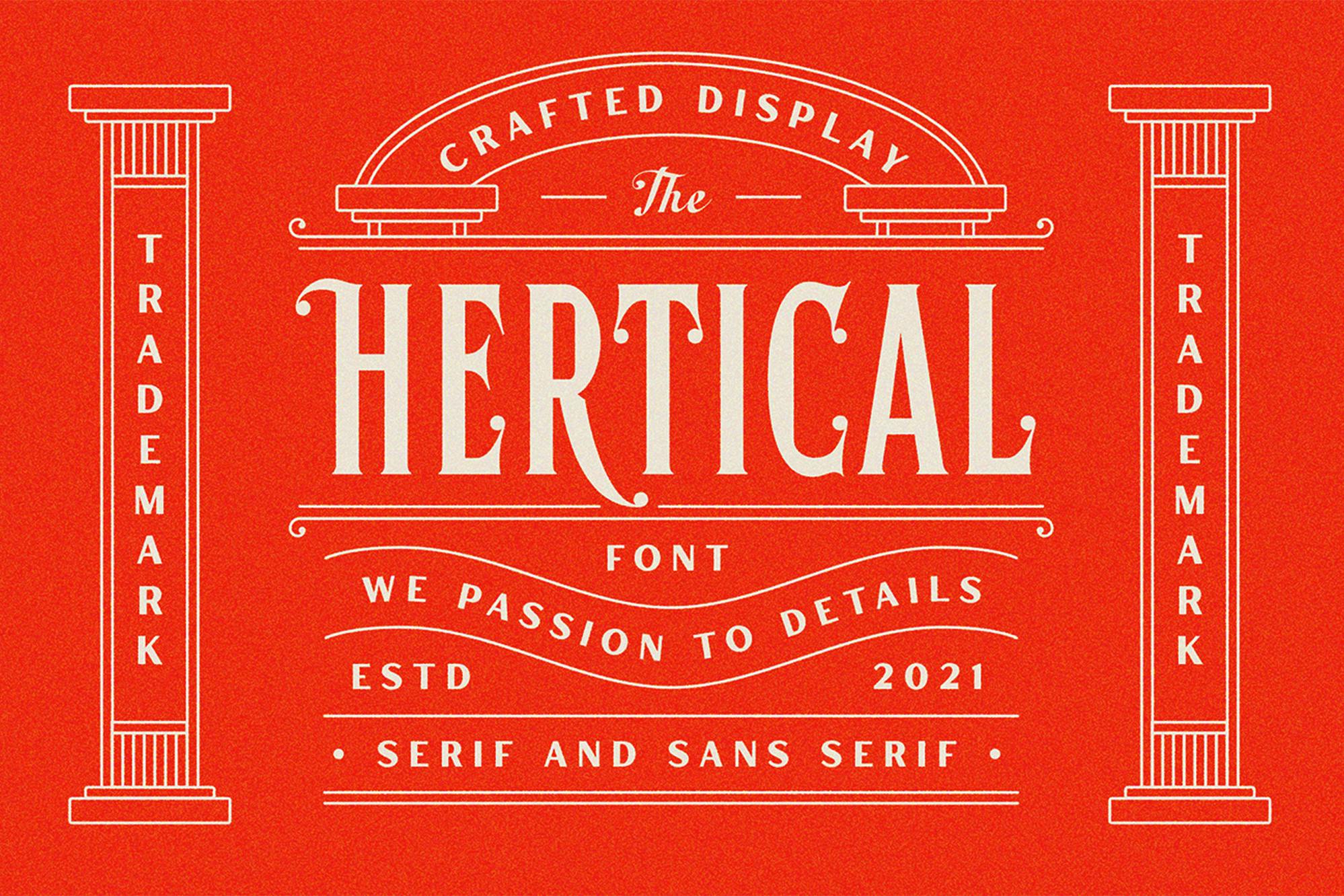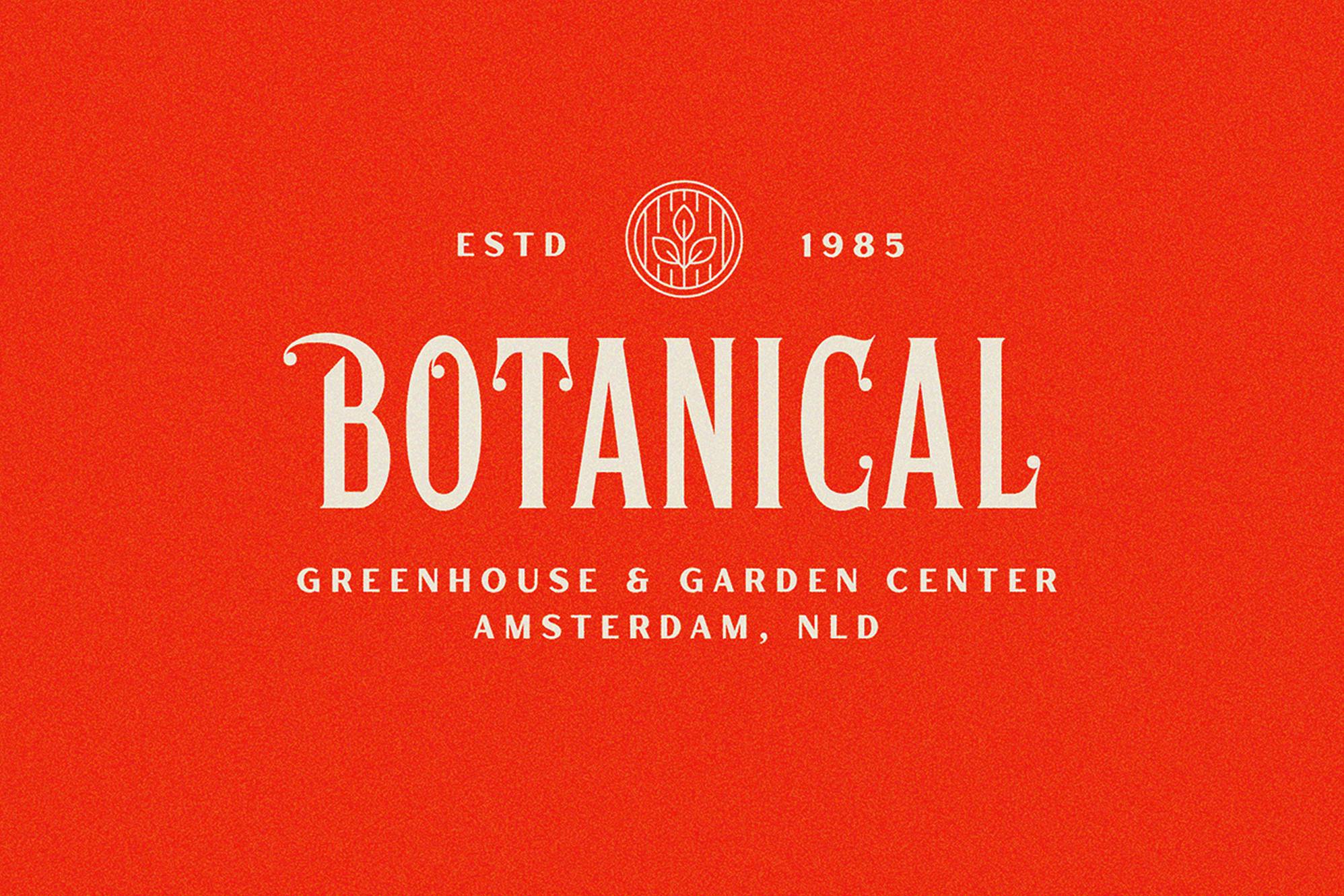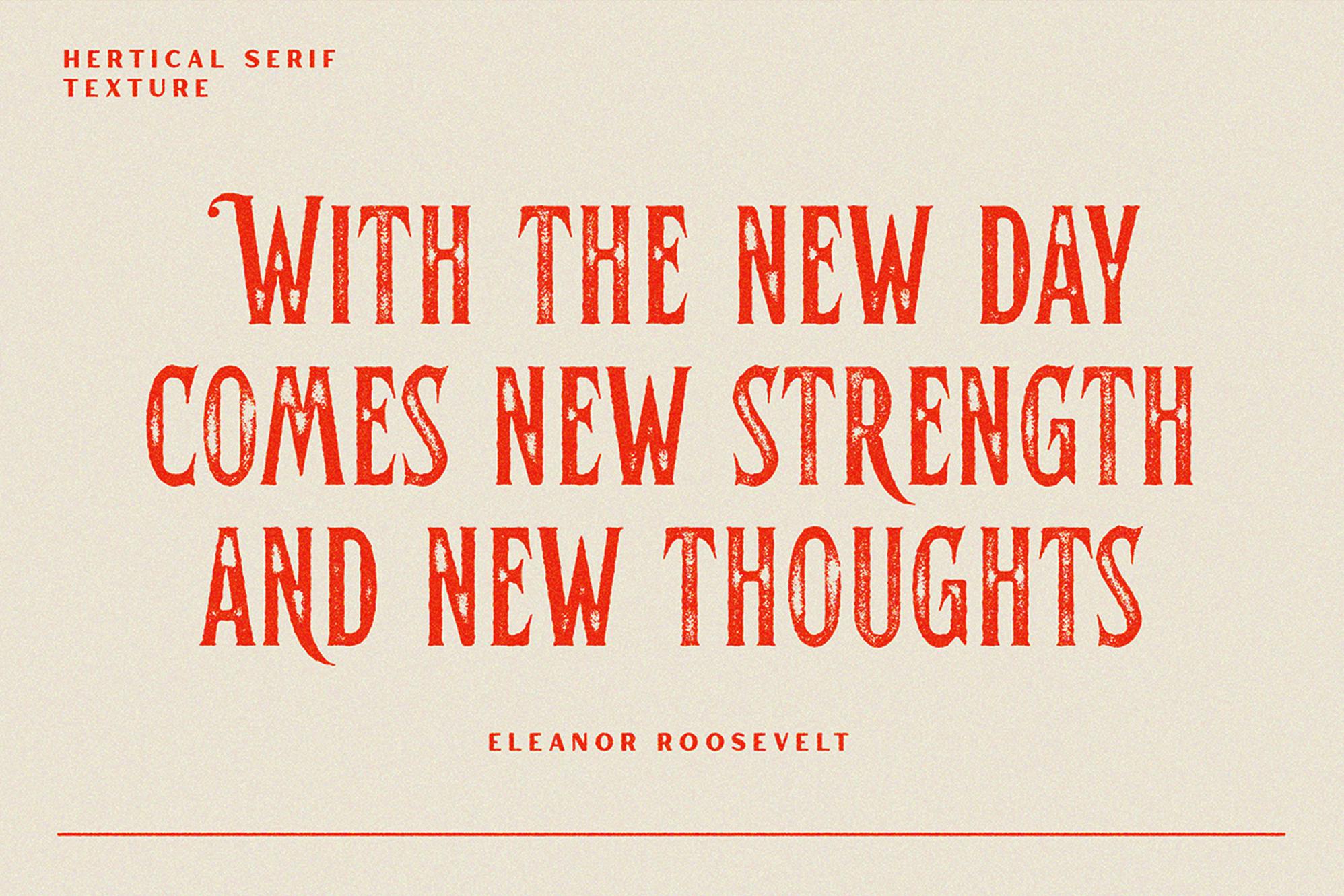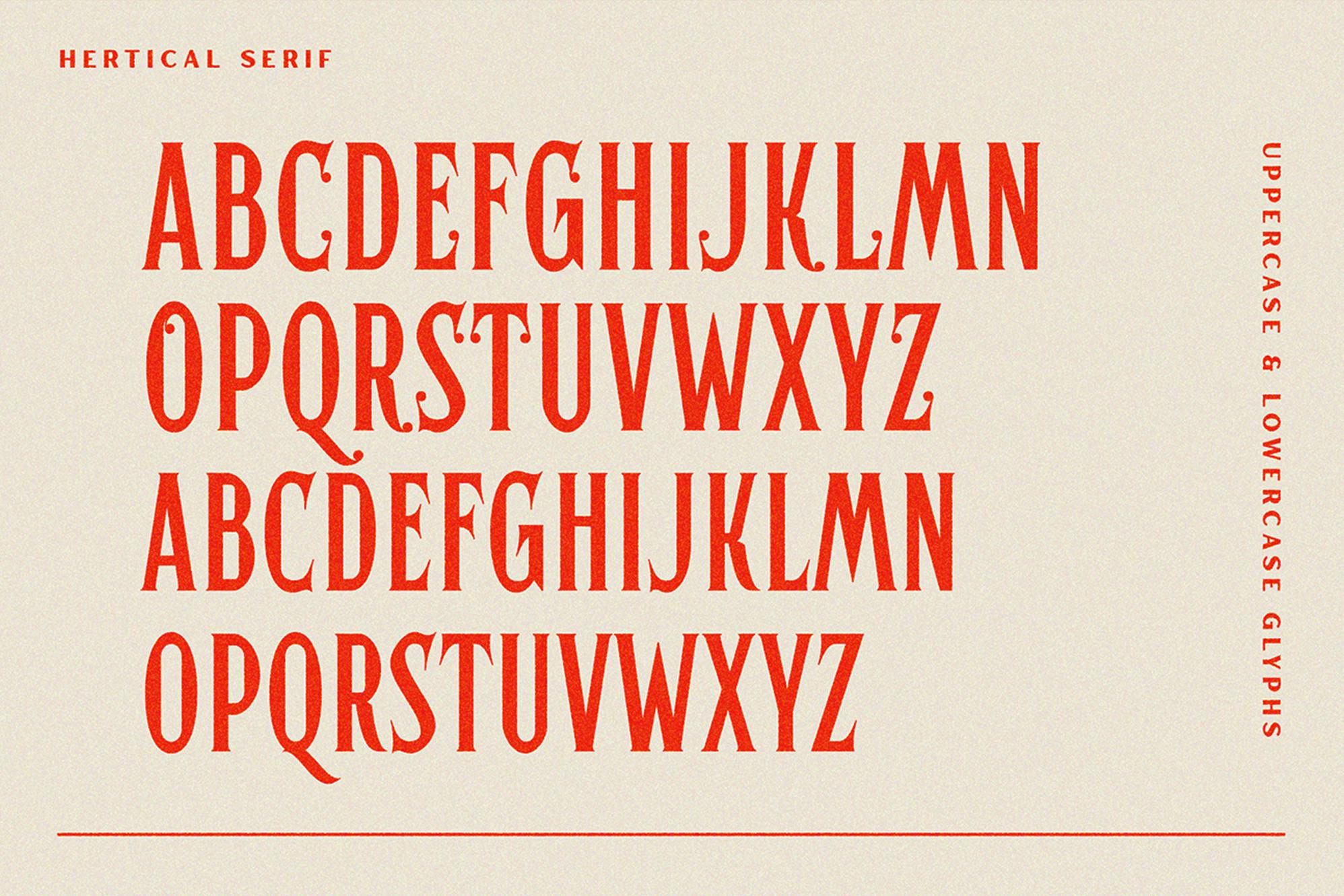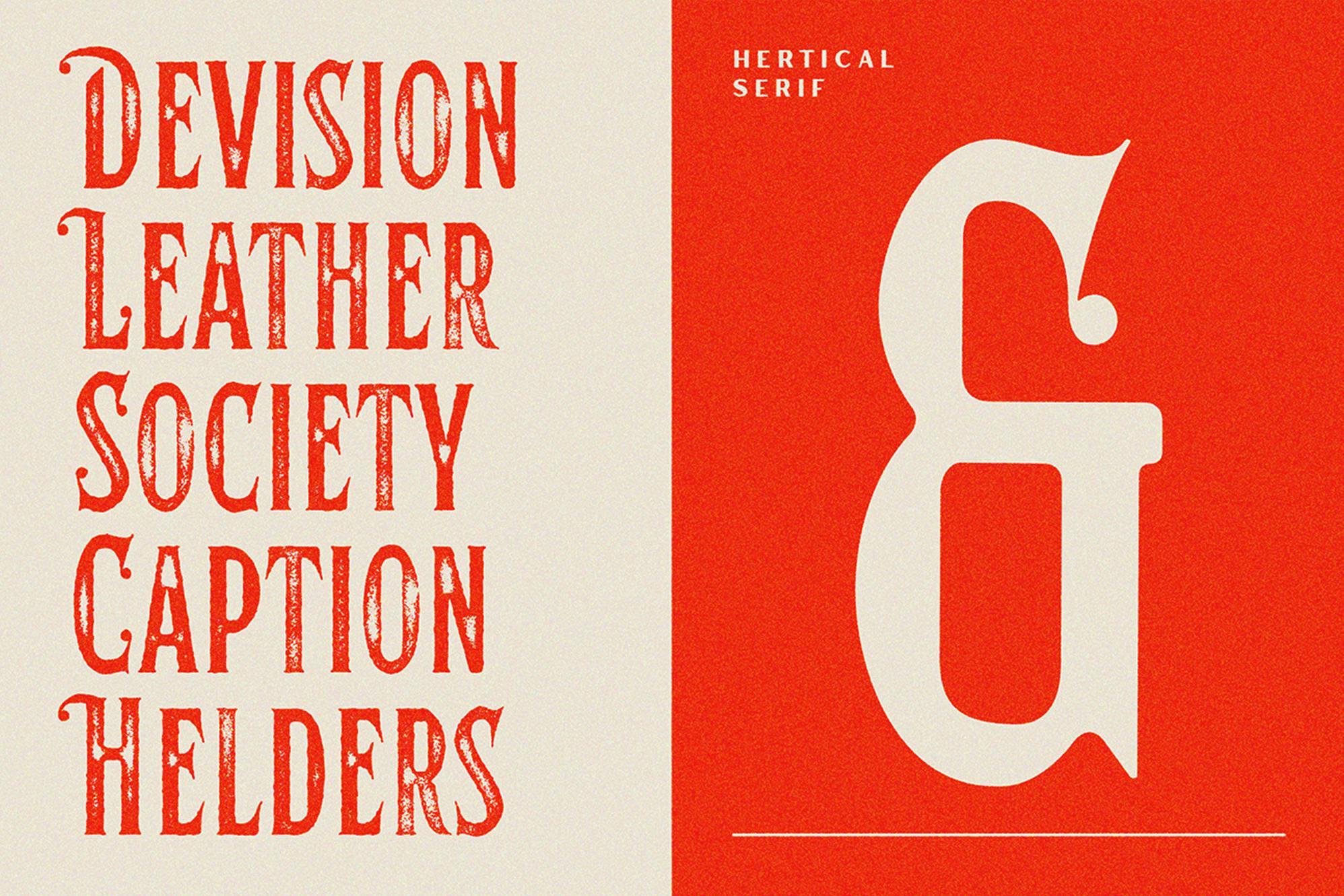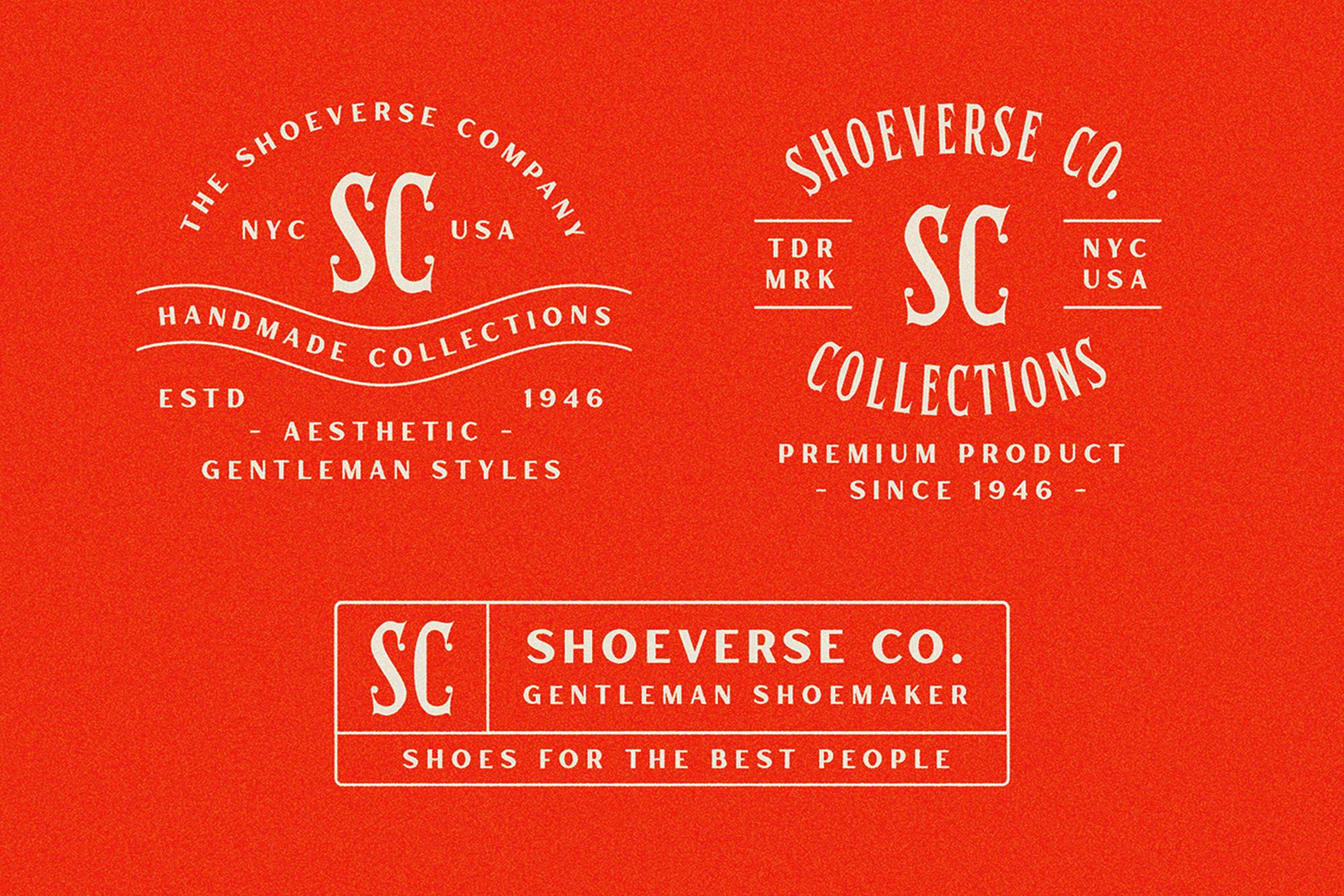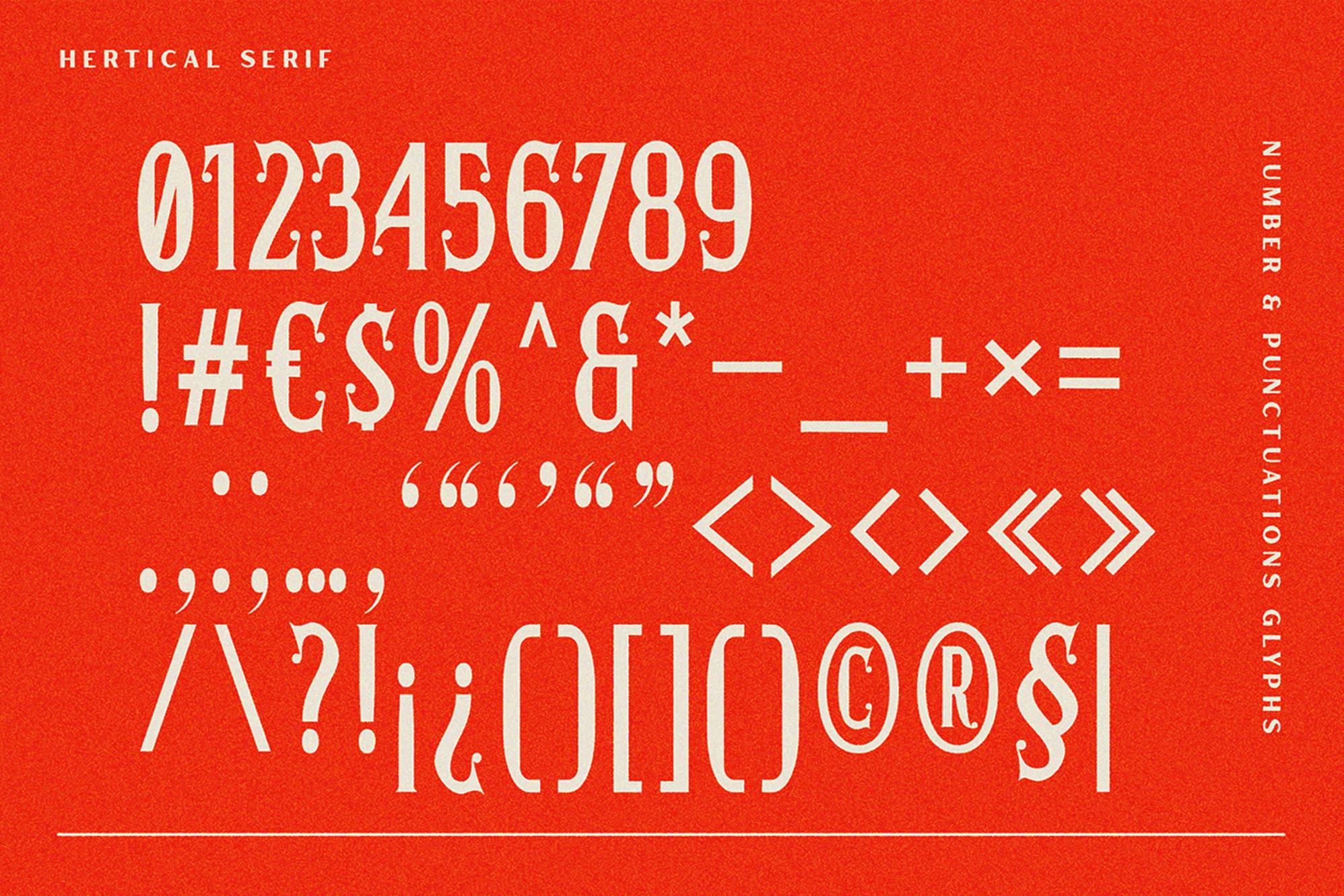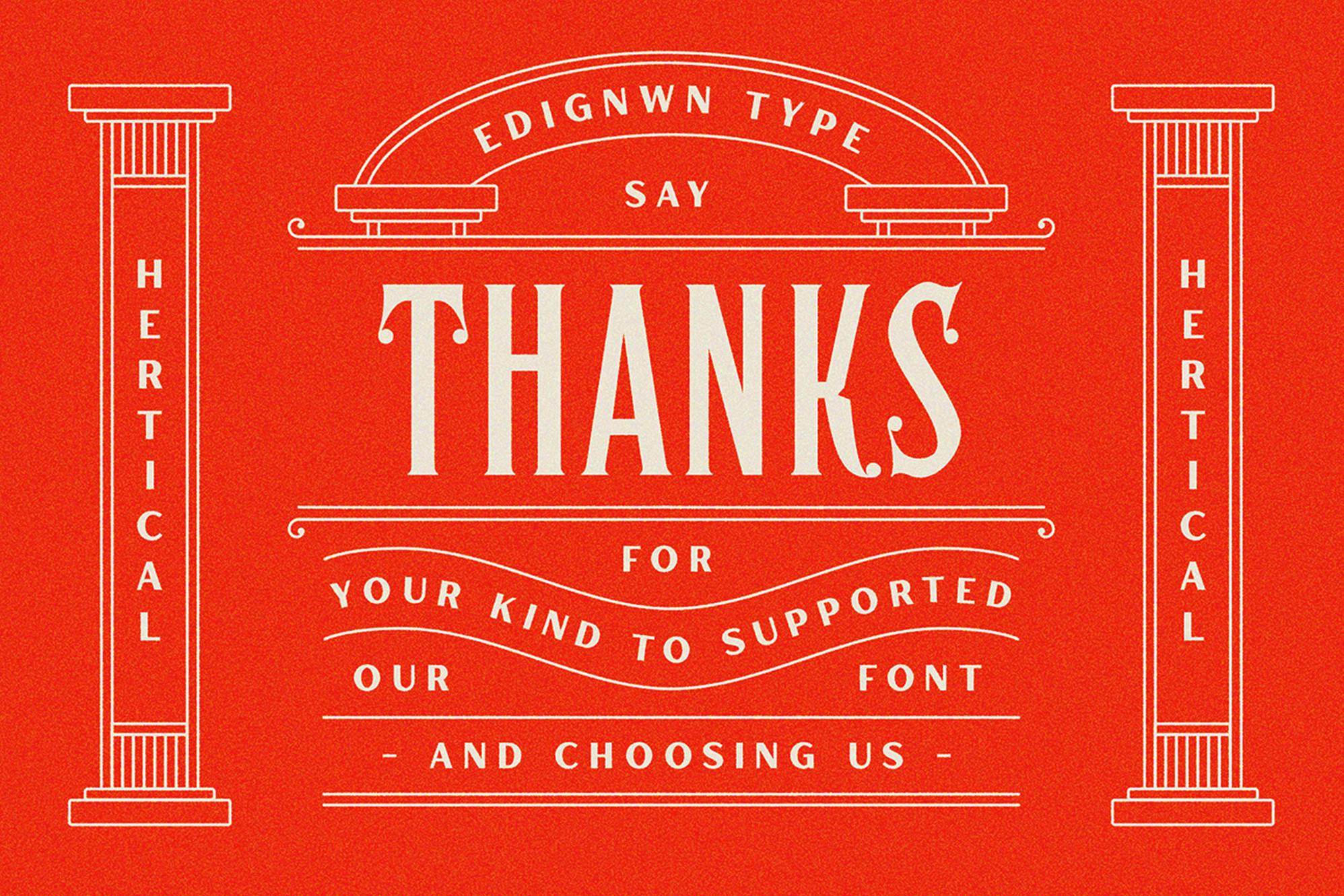
دانلود فونت نمایشی Hertical با دو نوع استایل
Hertical Crafted Display Font
فونت Hertical با دو نوع serif و sans serif، مناسب برای طراحی‌های خلاقانه.
فاصله گذاری Condensed | Normal
Hertical شامل دو نوع فونت، serif و sans serif می‌باشد. هر نوع فونت شامل چهار استایل (معمولی، صاف، زبر و بافت‌دار) است. این فونت‌ها برای طراحی‌های مختلفی مانند لوگو، پوستر، برچسب، نشان، بسته‌بندی، برندینگ، نقل قول‌ها و سایر طراحی‌های سفارشی مناسب هستند.
فونت Hertical شامل:
• 2 نوع فونت (serif و sans serif)
• 4 استایل فونت (معمولی، صاف، زبر و بافت‌دار)
• حروف بزرگ، اعداد، نمادها و علائم نگارشی
• 2 مجموعه جایگزین در فونت serif
• چند زبانه